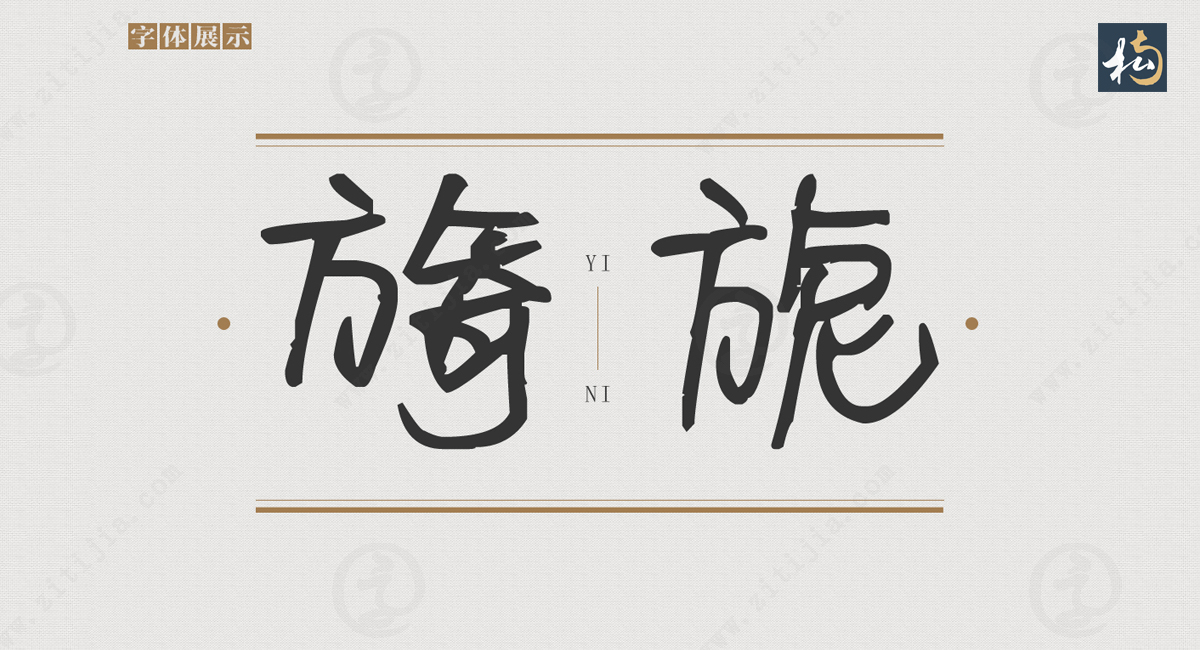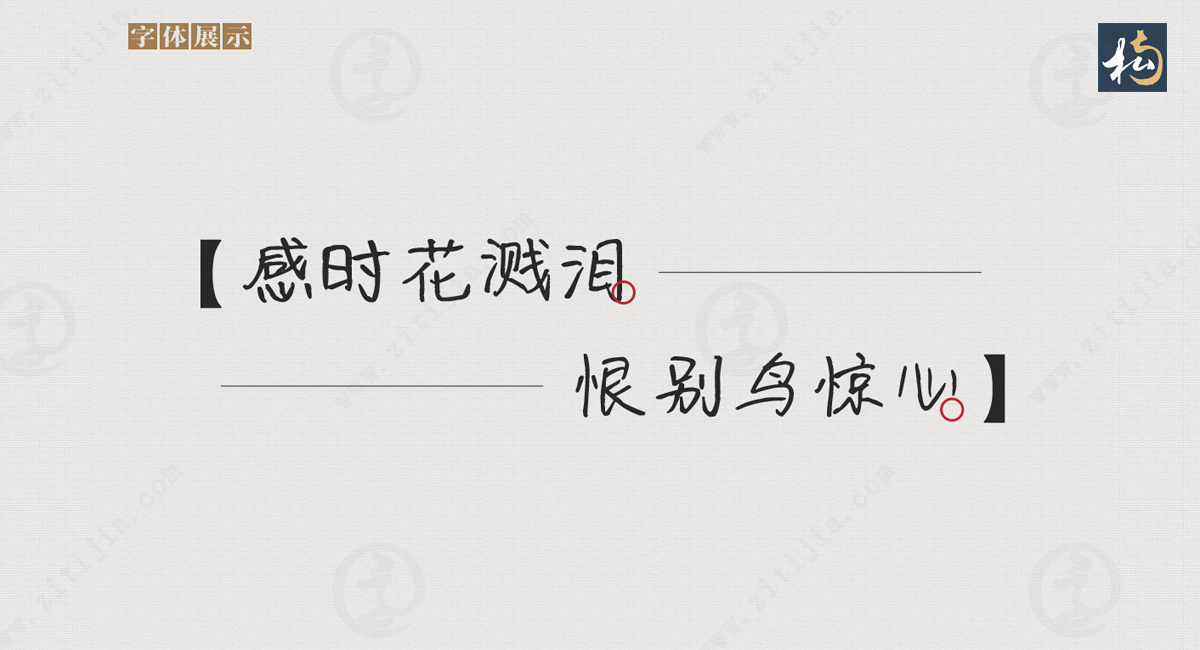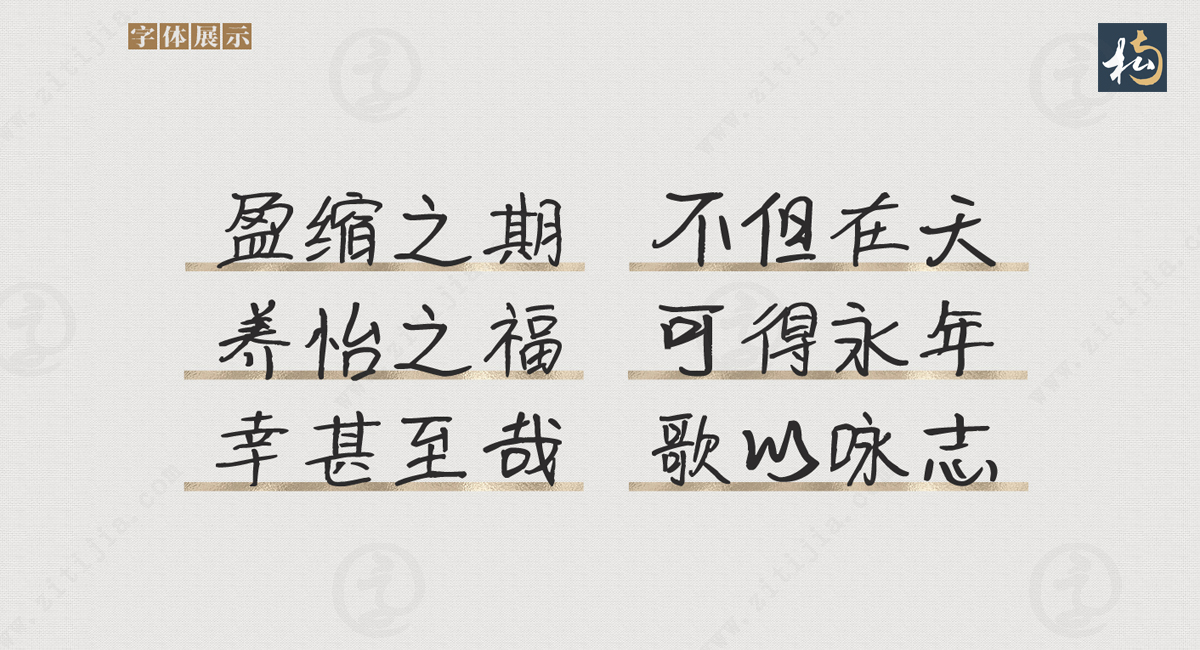
古朴、清新的行书风格,南构婷宜手写字体欣赏
南构婷宜手写字体是一种古朴、清新的行书风格字体。它的独特之处在于其硬笔手写的特点,使得它在书写字母时表现出了良好的规矩方正的特点。这种字体追求精致程度,在每个笔画中都能够展现出精美的细节和极致的美感。
南构婷宜手写字体的特点之一是它的字与字之间距离很小,这使得整体字体看起来更加紧密,让字体整洁有序。这种紧凑的排列方式使得文字在排版时能够充分利用空间,让设计更加高效。同时,紧密的字距离也使得每个字母之间的连接更加自然流畅,增强了整体字体的连贯性。
这款字体的另一个显著特点是它的清新自然。每个笔画都经过精心设计,使得字体呈现出一种自然的流动感。无论是直线还是曲线,每个笔画都被赋予了恰到好处的弯曲和转折,使得整个字体看起来生动而有趣。这种清新自然的特点使得南构婷宜手写字体非常适合用于各类文字设计和排版应用,能够给作品带来一种活泼而又不失庄重的氛围。
规矩方正也是南构婷宜手写字体的一个显著特点。每个字母都经过精确的构造和比例设计,使得字体整体呈现出一种规整的美感。每个笔画的长度和宽度都经过精确计算,使得字母之间的比例和平衡感非常好。这种规矩方正的特点使得南构婷宜手写字体在正式场合和商业设计中都能够展现出专业和可靠的形象。
总的来说,南构婷宜手写字体具有清新自然、规矩方正、精致优美的特点。它的硬笔手写风格使得每个字母都展现出了良好的规矩方正,同时又能够表现出精美的细节和极致的美感。无论是在文字设计还是排版应用中,南构婷宜手写字体都能够为作品增添一份独特的魅力和品味。无论是用于印刷品还是数字媒体,这款字体都能够展现出其独特的风格和个性,成为设计师们的首选之一。
南构婷宜手写